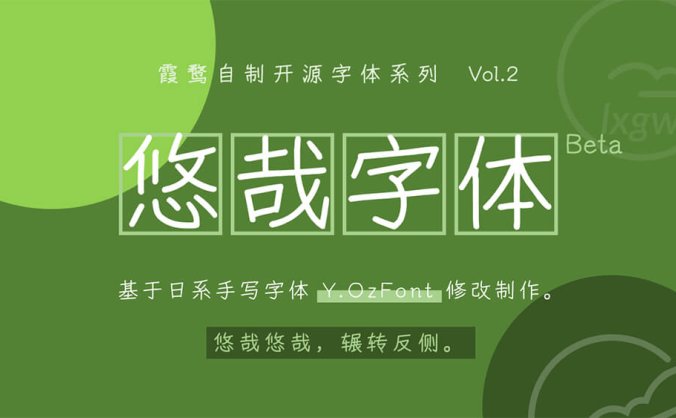
《悠哉字体》基于日系手写字体 Y.OzFont修改制作
字体简介: 悠哉字体是一款基于Y.OzFont的手写风格的字体。利用原字体中已有的笔划和部件,通过拼接和调整造出新字 (必要时自己用鼠标写出部件) 。目前已补全原字体中有对应繁体字的简体字,以及GB 2312范围内的所有汉字,并根据jf Open 粉圆的字库补全了繁体中文的常用汉字 (包含台湾教育部门规定的 4808 个常用汉字) 。 悠哉字体在原Y.OzFont的基础上,字面缩小至原来的95%,…- 1.2k